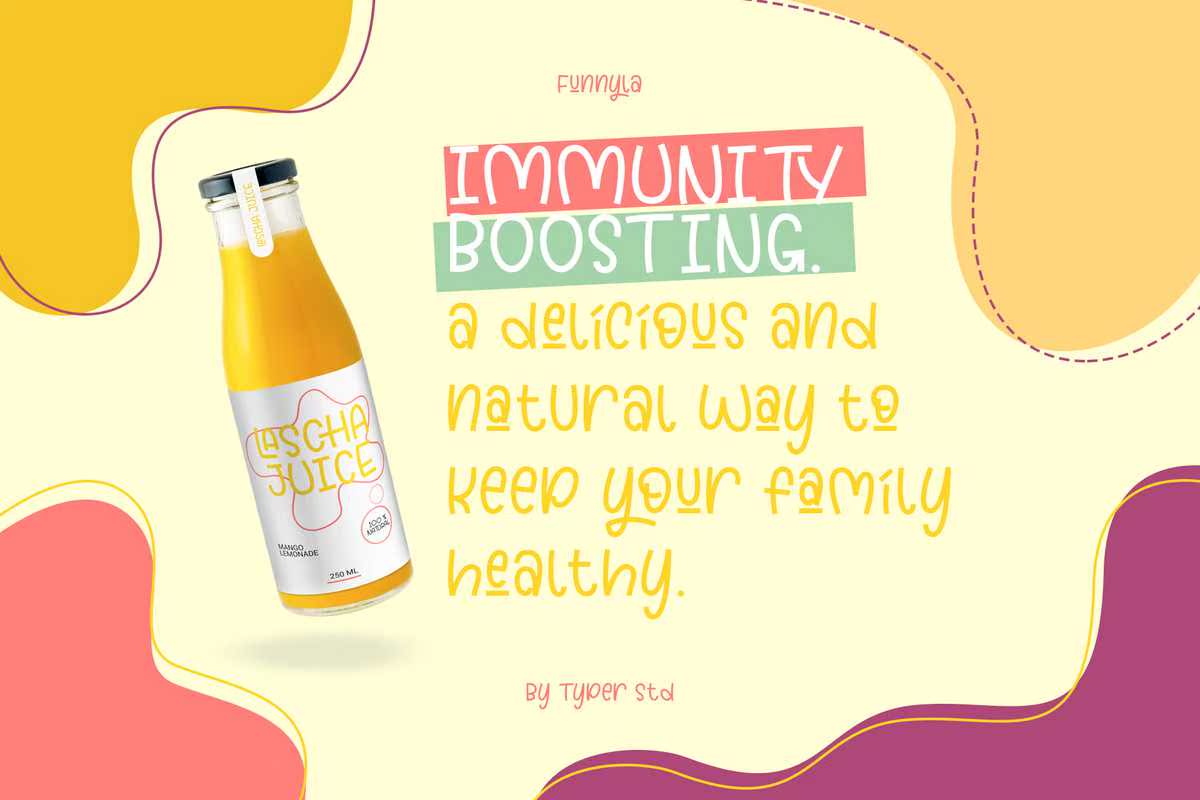
我们最新的产品:FunnylaFont with the Tute and Catchylook,让您的设计更具趣味性,使用时尚的连接器和替代品!非常适用于包装、报价、印刷项目、广告和一些展示工艺。自豪地展示我们最新的产品:FunnylaFont with the Cute and Catchylook,让您的设计更具趣味性,使用Tylistic Ligature和Alternate!伟大的包装,报价,印刷项目,广告和一些展示工艺。